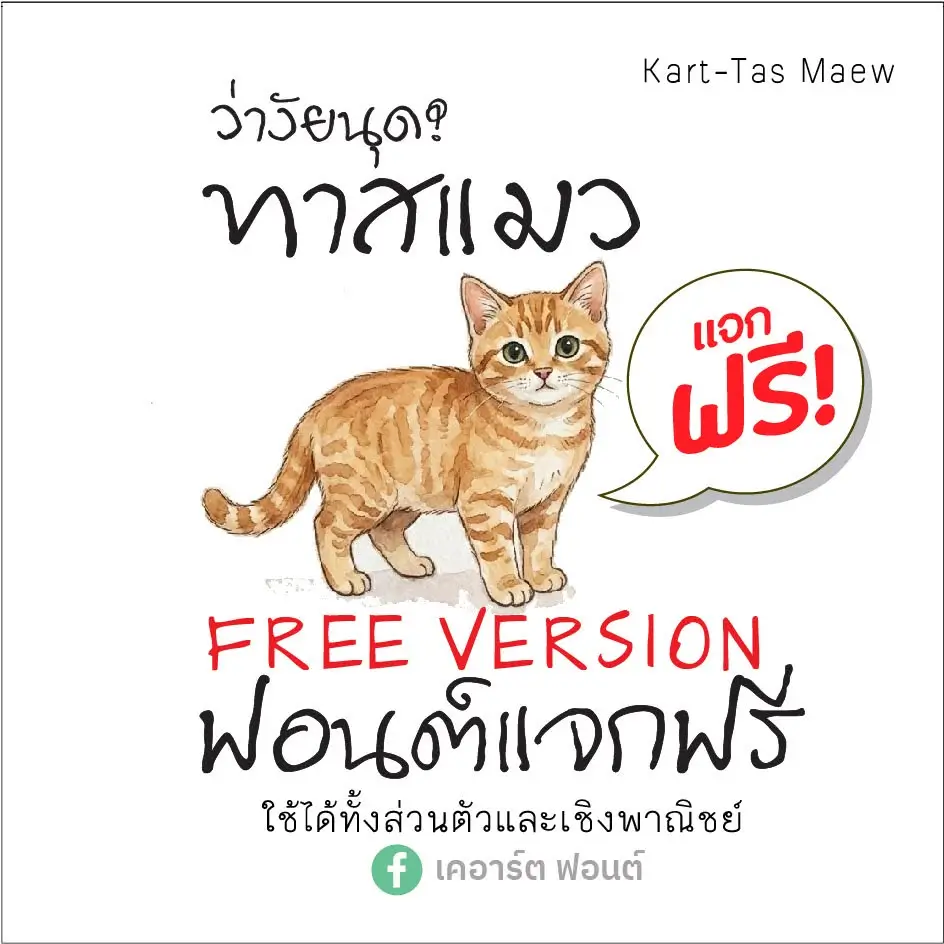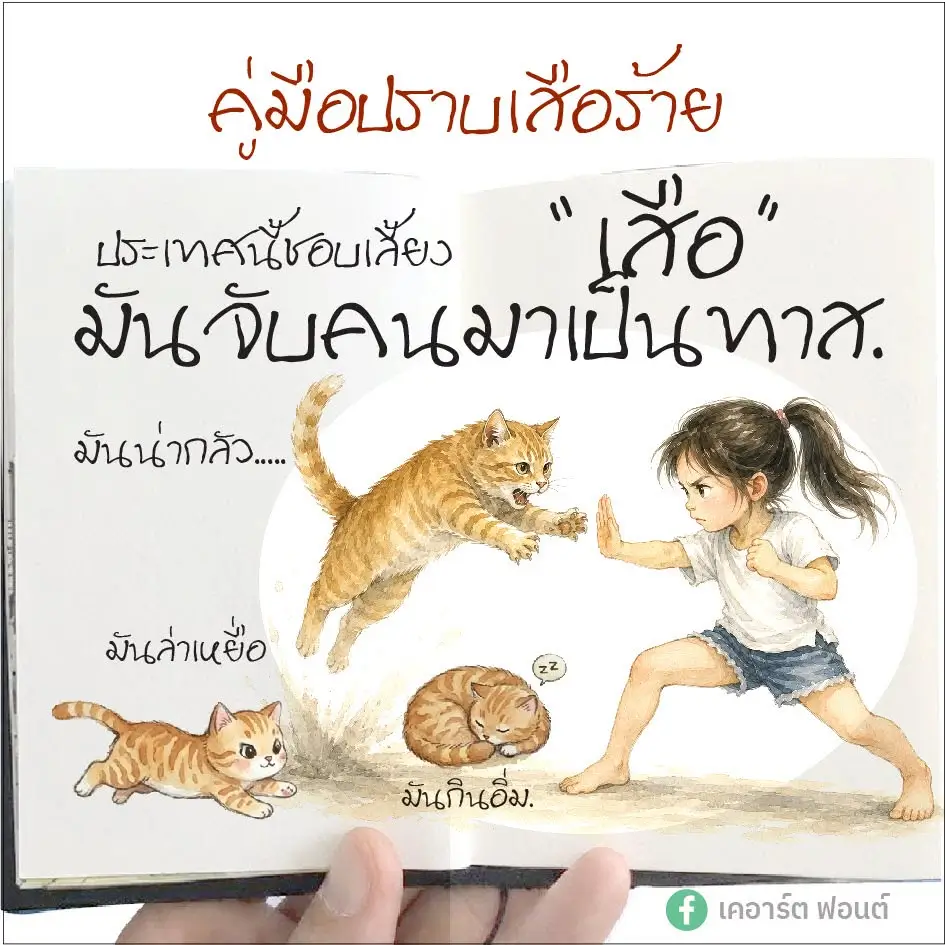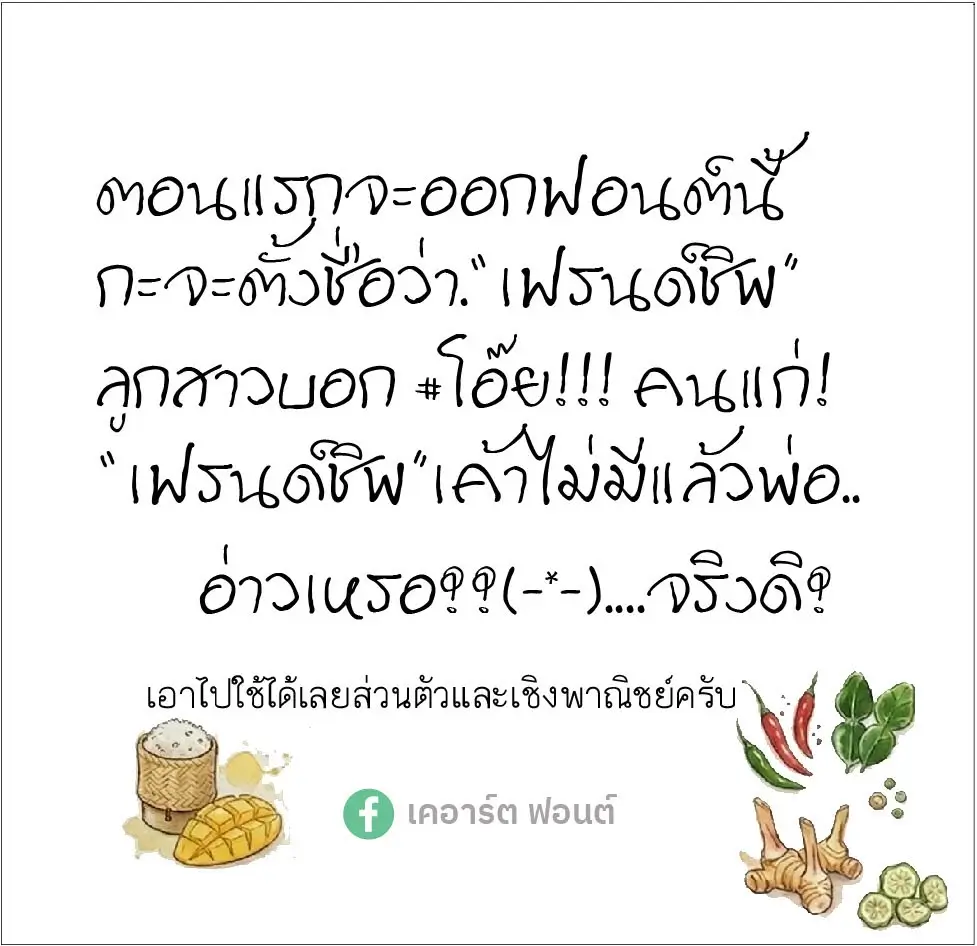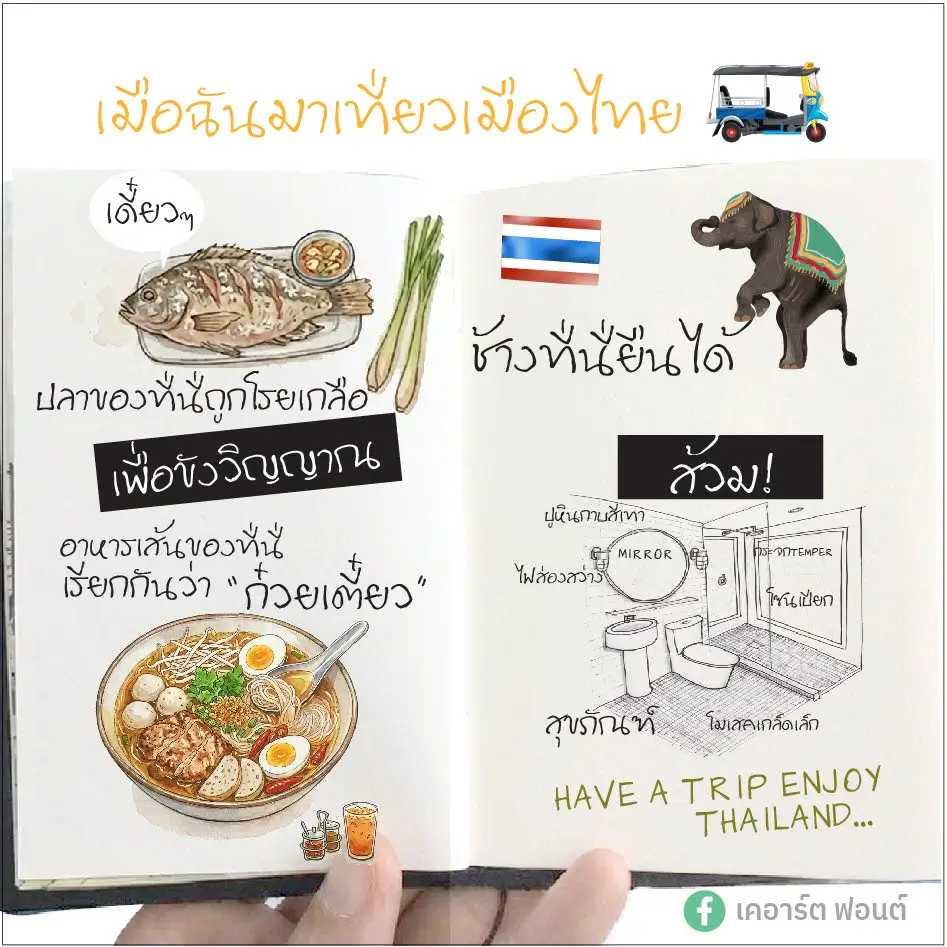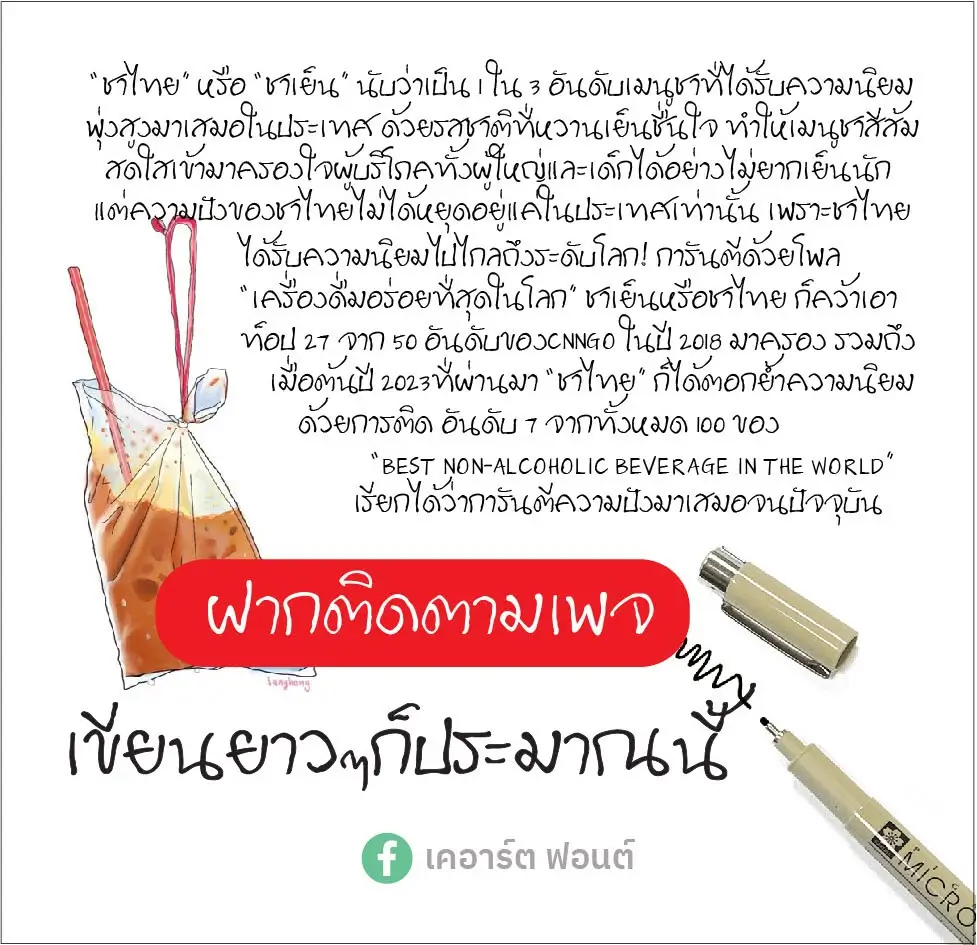
ทาสแมว (Kart-TAS MAEW)
ฟอนต์ เคอาร์ต-ทาสแมว (Kart-TAS MAEW) – เป็นฟอนต์ที่เขียนแจกฟรีครับ #ฟอนต์ลายมือเด็ก สามารถใช้ครอบคลุมหลายโปรแกรมใช้ได้ทั้งส่วนตัวและเชิงพาณิชย์  สนับสนุนผลงานโดเนตได้ครับ